今回はタイププロジェクトのInstagramから文字の「点」を集めた投稿の紹介です。「点」は文字の中の小さな要素ですが、それでもきちんとその書体らしさが出ています。
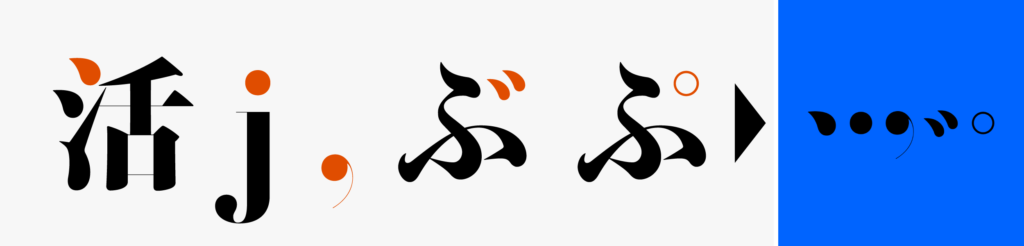
あつめた「点」は以下の5種類です。
「活」の一画目
「j」の点
「,」コンマ
「ぶ」の濁点
「ぷ」の半濁点
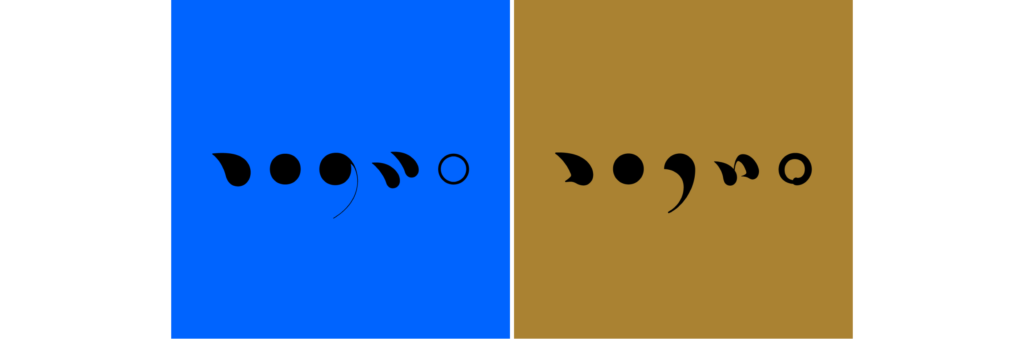
左は濱明朝 ディスプレイ H、右は金シャチフォント 姫 Bの点です。
濱明朝 ディスプレイはコンマの点から出ている線がとても細いです。同じ濱明朝でもテキストやキャプションだともう少し太めにデザインされています。
金シャチフォント 姫は濁点に筆の流れが表現されています。半濁点も筆で書いたようなデザインです。明朝体など仮名が筆で書いたようなデザインの書体でも、半濁点についてはコンパスで書いたような円であったりするので、この半濁点のデザインは金シャチフォント 姫の特徴の一つであると思います。
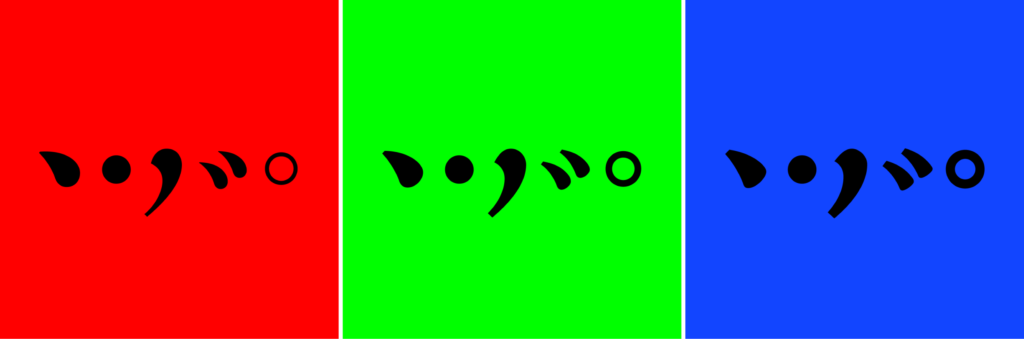
左からTP明朝 ハイコントラスト H、ミドルコントラスト H、ローコンラスト Hの点です。
「活の一画目」と「ぶの濁点」を見てみると、ハイコントラストではツルッと正円が入りそうなデザインで、対してローコントラストではやや角ばったデザインになっています。
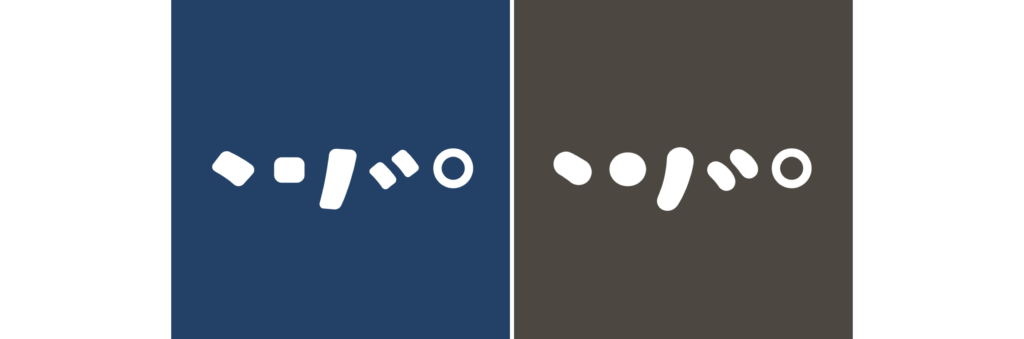
左がAXISラウンド 50 H、右がAXISラウンド 100 Hの点です。
「jの点」や「ぶの濁点」を見ると、ラウンド 50よりラウンド 100の方が大きく作られています。 これは組版の中で丁度良いバランスで見えるよう調整したためで、このように拡大してじっくり見てみないと気づかないかもしれません。
ちなみにこの画像の製作中、5種類の点が横一列で等間隔に並んで見えるよう調整していた時は、フォントのツメ情報を設定してる時と同じ感覚でいました。